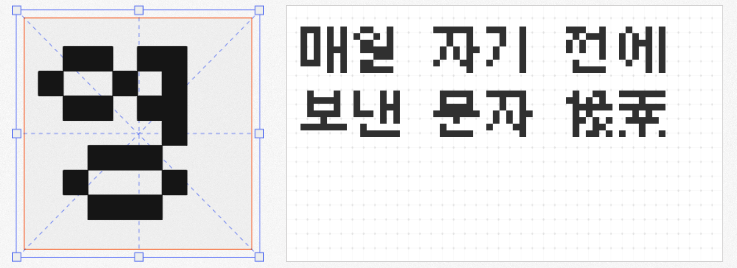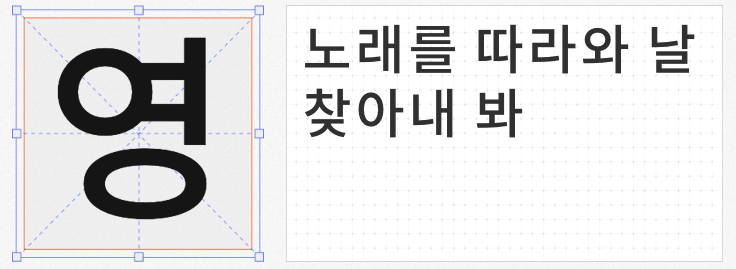
在全球化设计浪潮中,韩文字体以其独特的文化符号与视觉张力,成为品牌叙事与视觉传达的重要载体。以下四款免费商用韩文字体,既承载着韩国传统文化的基因密码,又以现代设计语言重构视觉表达,为设计师提供兼具文化深度与实用价值的创意工具。
这款字体以韩国传统建筑与服饰为灵感源泉,将韩屋屋顶的波浪形曲线与韩服缎带袜的流畅线条,抽象化为笔画的动态韵律。其设计突破常规韩文字体的几何框架,通过曲直交融的笔画处理,赋予文字以建筑般的立体感与服饰般的柔美气质。无论是文化海报的标题设计,还是传统品牌包装的视觉呈现,都能以独特的文化符号唤醒受众的情感共鸣。
作为基于Pretendard Std、思源黑体与秋空黑体MN融合优化的开源字体,檎风黑体以极简的几何结构与均衡的笔画粗细,构建出清晰锐利的现代视觉语言。其设计兼顾屏幕显示的清晰度与印刷场景的适应性,尤其适合科技、教育等领域的国际化设计需求。作为CJK(中日韩统一表意文字)通用字体,更可实现多语言排版的无缝衔接。
以首尔地标“南山”命名的这款字体,将儒生精神的内敛与韩屋瓦片的曲线美学融入字形设计。其笔画端庄中蕴含灵动,留白处暗藏韵律,通过传统建筑的比例美学与现代字体的结构优化,塑造出兼具历史厚重感与当代审美趣味的视觉形态。特别适合文化旅游、城市宣传等需要传递地域文化认同的场景。
受任天堂DS游戏机字体启发的这款位图字体,以8-bit像素风格重构韩文字形。其设计通过精确的像素排列与模块化组合,在保持复古游戏美学的同时,确保文字的可读性与设计延展性。无论是游戏界面、数字艺术装置,还是怀旧主题的视觉设计,都能以独特的像素质感营造沉浸式体验。
这四款字体既是对韩国文化基因的视觉解码,也是现代设计思维的创意实践。无论是追求文化深度的品牌叙事,还是需要高效排版的商业项目,这些免费商用的优质资源都能为设计注入鲜活的生命力。